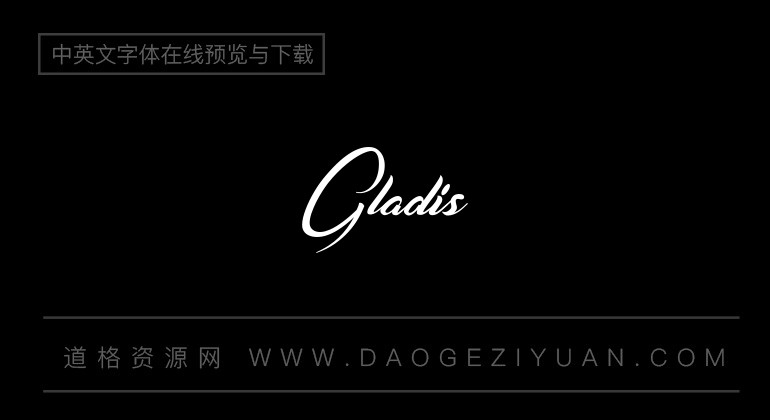
Gladis是一种装饰性字体,具有优美的流线型字形和强烈的视觉冲击力。它的特点是字母之间的连接和重复形式,使得它具有独特的视觉效果。该字体由设计师Olivier Gourvat创造,为商用和个人项目提供了许多字重和样式选项。Gladis适合于海报、标志、包装和其他需要吸引眼球的设计项目。内容介绍
Gladis是一款非常不错的手写艺术字体,具有很好的视觉感,适合于文化类的宣传设计、商业类品牌的广告和产品包装设计以及个性化文字排版等较多场景。